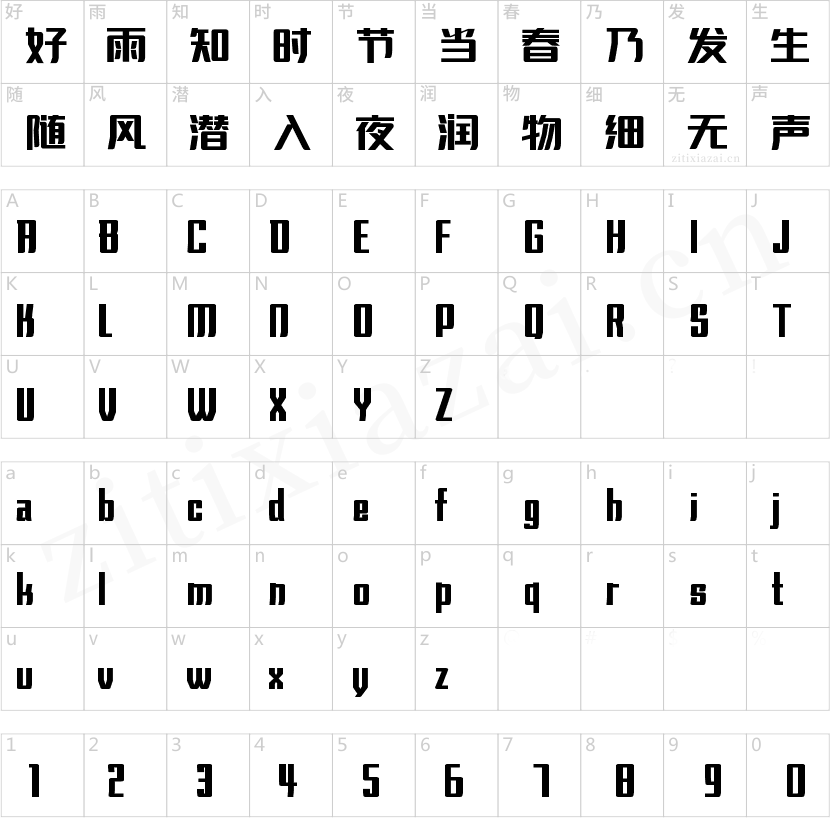
字魂活力飞扬体
字魂活力飞扬体,这款字体结构工整、笔画清晰,兼顾美观与易读性,适用于标题、正文、海报、包装、LOGO 等多种场景。字形优雅稳定,风格百搭耐看,适配日常排版与创意设计,让文字呈现更舒适、更具质感。字魂活力飞扬体一笔一画,皆是细节,以均衡的比例、流畅的线条打造舒适视觉体验,字形端正大气,风格简约现代。无论是商业设计、品牌宣传还是日常排版,都能轻松驾驭,让文字更有格调与力量。字魂活力飞扬体字体下载。
字魂字体字小魂活力飞扬体字体是由字魂创意字库设计并生产的一款可商用的字体,被收录于字小魂系列。该字体支持GB-2312标准,包含6763个中文、字母、符号和数字,字体类型偏向黑体,具有活泼、时尚的风格,在市面上广泛用于企业文化、VI、视频综艺等场景。